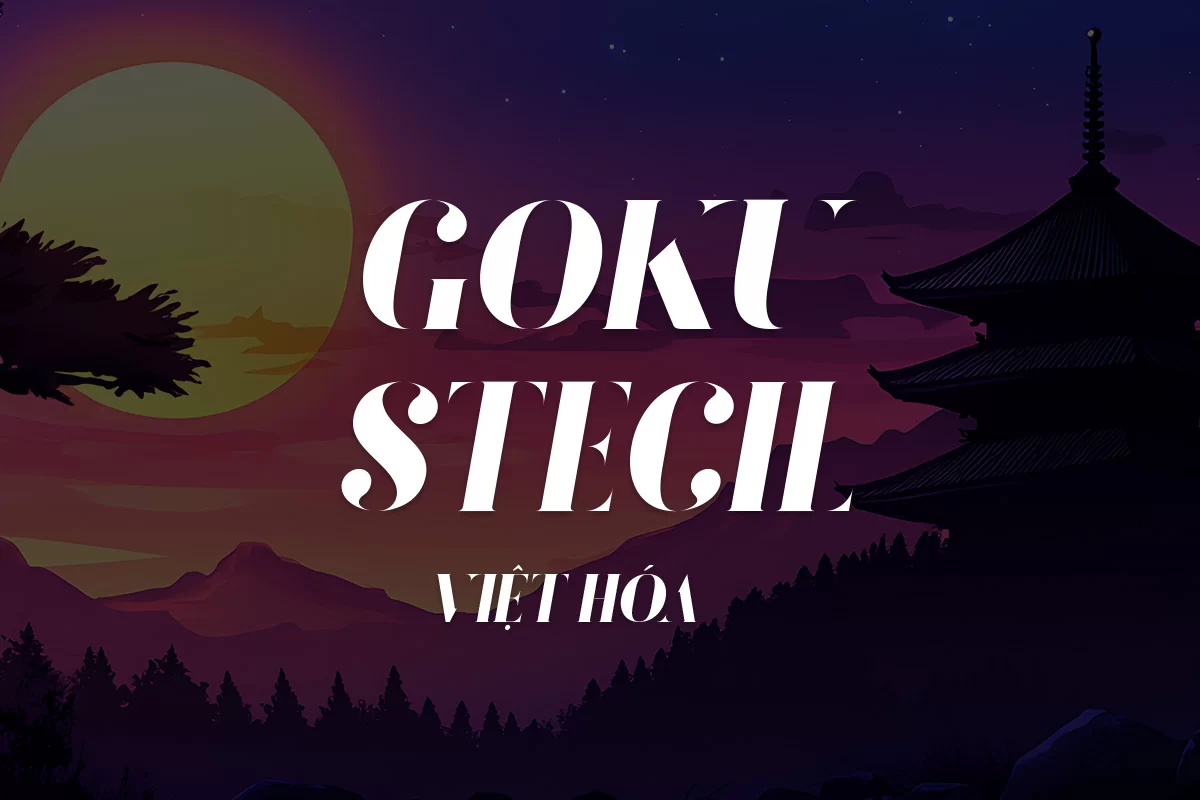
GOKU STENCIL Việt hóa là font chữ mang phong cách stencil hiện đại, nổi bật với các nét cắt táo bạo và hình khối dứt khoát. Thiết kế của font vừa mang cảm giác mạnh mẽ, chiến binh vừa có sự sáng tạo nghệ thuật, tạo ấn tượng ngay từ cái nhìn đầu tiên. Bộ font này đặc biệt phù hợp cho các poster phim, bìa game, thiết kế quảng cáo, tiêu đề tạp chí, banner sự kiện hoặc bất kỳ dự án nào cần một phong cách ấn tượng, độc đáo và đầy khí chất.
Phiên bản Việt hóa hỗ trợ đầy đủ dấu tiếng Việt, giúp bạn dễ dàng ứng dụng trong các thiết kế mang bản sắc Việt mà vẫn giữ nguyên sự mạnh mẽ vốn có của font gốc.